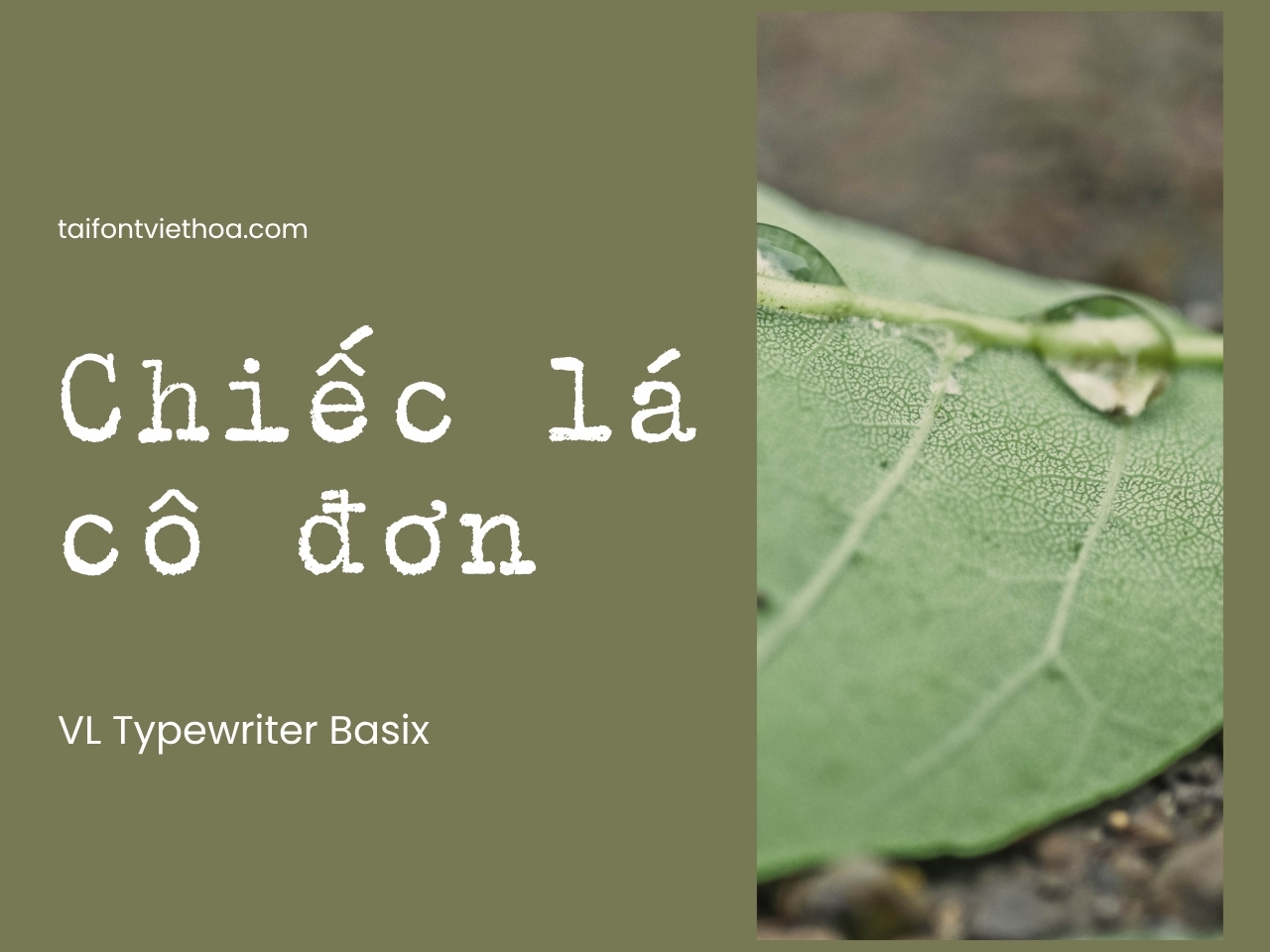
Font việt hóa VL Typewriter Basix đầy đủ
Tác giả Font: Matthias Luh
Giới thiệu về font VL Typewriter Basix
VL Typewriter Basix là một bộ font mang phong cách đánh máy cổ điển, lấy cảm hứng từ các máy đánh chữ thập niên 60–70. Với cấu trúc đơn giản, mạnh mẽ và độ đều nét cao, font này gợi nhớ đến sự mộc mạc, chính xác và tinh thần báo chí truyền thống. Phiên bản Việt hóa trọn bộ được thực hiện bởi Font Việt Linh, hỗ trợ đầy đủ tiếng Việt với hệ dấu được căn chỉnh tỉ mỉ. Ngoài tiếng Việt, font còn tương thích với hơn 50 ngôn ngữ khác nhờ bảng mã Latin mở rộng. VL Typewriter Basix đã được taifontviethoa.com sưu tầm, kiểm nghiệm và đưa vào ứng dụng thực tiễn trong các thiết kế mang phong cách cổ điển, báo chí, và dự án retro cá tính.
Đặc điểm thiết kế và ứng dụng của VL Typewriter Basix
Font sở hữu kiểu dáng đơn giản, mang tính kỹ thuật cao với các ký tự có chiều cao đồng đều, đậm nét và mang tính chức năng rõ rệt. Các chi tiết mô phỏng máy đánh chữ giúp tăng tính hoài niệm và cổ điển, rất phù hợp với thiết kế mang thông điệp xưa cũ hoặc đậm chất biên tập.
VL Typewriter Basix phù hợp cho thiết kế poster phim retro, sách báo cổ, tạp chí nghệ thuật, bìa sách văn học, giao diện website mang phong cách vintage hoặc các chiến dịch marketing lấy cảm hứng từ thời kỳ analog. Ngành nghề lý tưởng: xuất bản, truyền thông, thời trang cổ điển, thiết kế sáng tạo và sản phẩm mang giá trị hoài niệm.